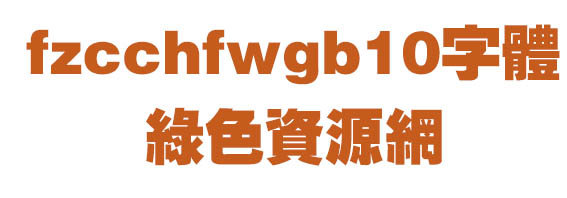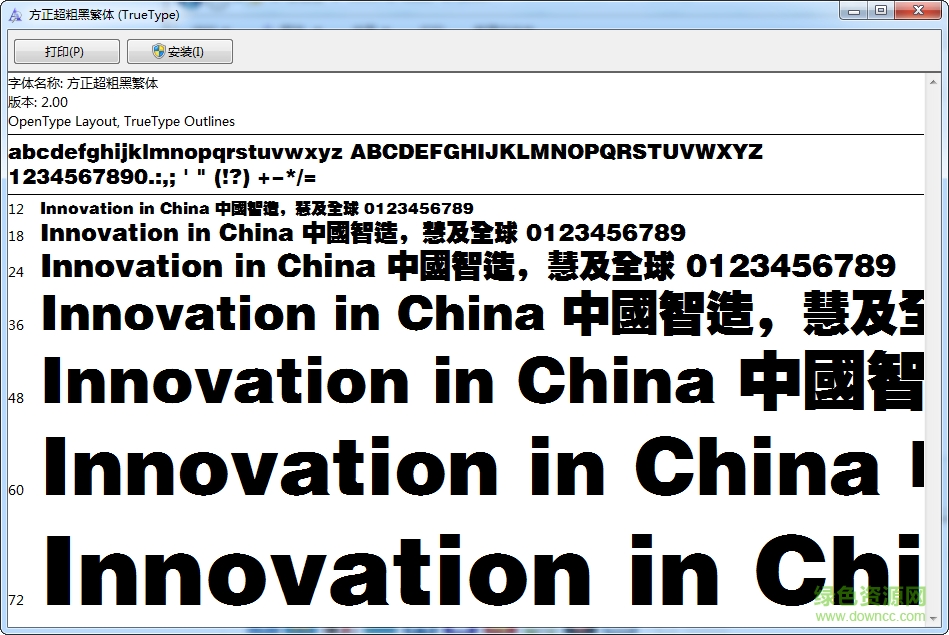
fzcchfwgb10字體是一款非常實(shí)用的字體,這款字體也是方正字體中的一種哦,方正超粗黑繁體,喜歡繁體字的朋友不要錯(cuò)過這款字體啦,有需要的就來綠色資源網(wǎng)下載吧!
fzcchfwgb10字體整體呈現(xiàn)的是一種比較粗的字體,并且略帶有繁體字的優(yōu)美,給人一種大氣美觀